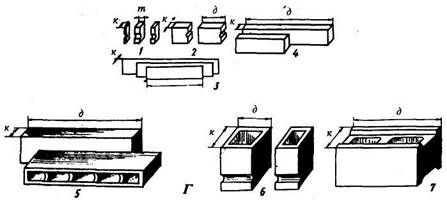
Типографский шрифт
А. Буквы: 1 - основные элементы; 2 -соединительные элементы; 3 - засечки
Б. Элементы строки: 1 - нижняя линия строки; 2 - верхняя линия строки; 3 - линия прописных букв; 4 - нижние выносные элементы; 5 - верхние выносные элементы; 6 -надстрочные элементы
В. Литера: 1 - сигнатура; 2 - тело литеры; 3 - очко; 4 -головка; 5 - ножка
Г. Пробельный материал: 1 - шпации; 2, 6 - бабашки; 3 - шпоны; 4 - реглеты; 5 - марзаны; 7 - пробельные марзаны; к - кегль; д - длина; т - толщина